原文标题:期末考试阅卷老师最厌恶的几种字体,你家孩子中枪了吗?
期末考试来了,以下是最让阅卷老师讨厌的几种字体,一般遇到这样的字,老师会扣分的。快来看看有没有你家孩子写的字的影子?你家孩子写的字是图几的样子?
如果没有,小英老师恭喜孩子卷面分可以得到,如果有,那就要在考场上尽量避免,考试完,练字的计划就得提上日程啦。
1、远距离的恋爱式:
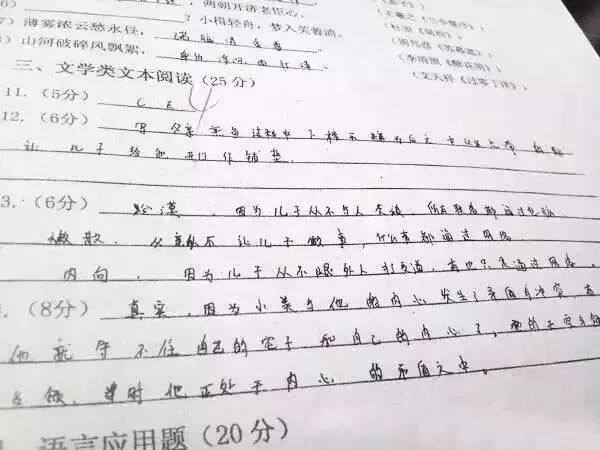
2、黑蚂蚁的飞行式:
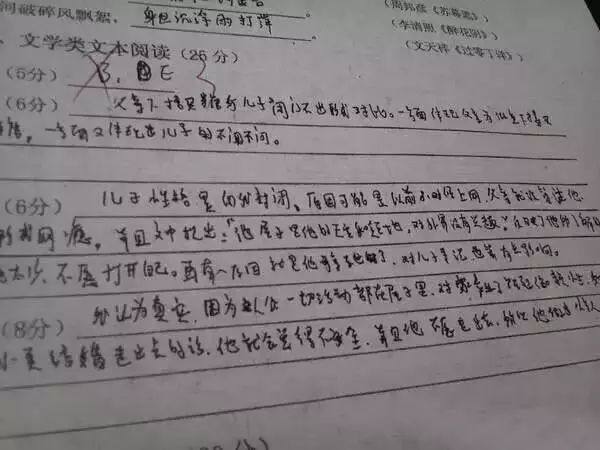
3、深坑寻幽式:
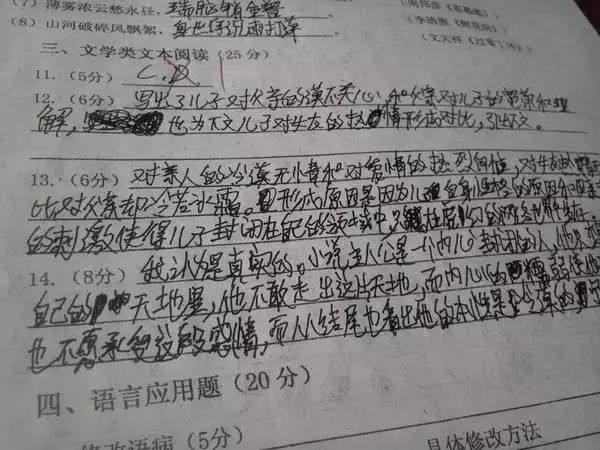
4、卑微的木柴式:
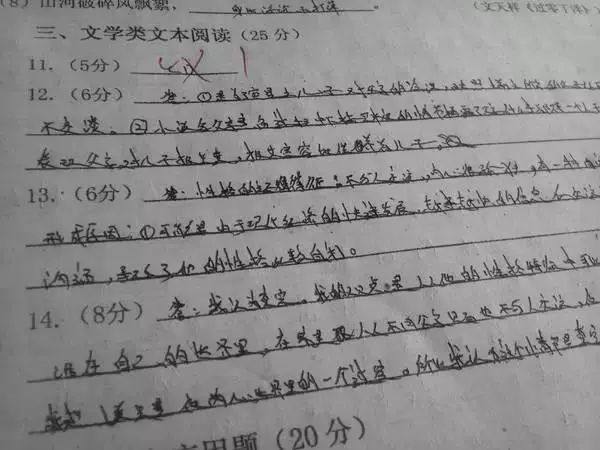
5、蓝色颤抖式:(中高考理论上只能用黑色水笔)
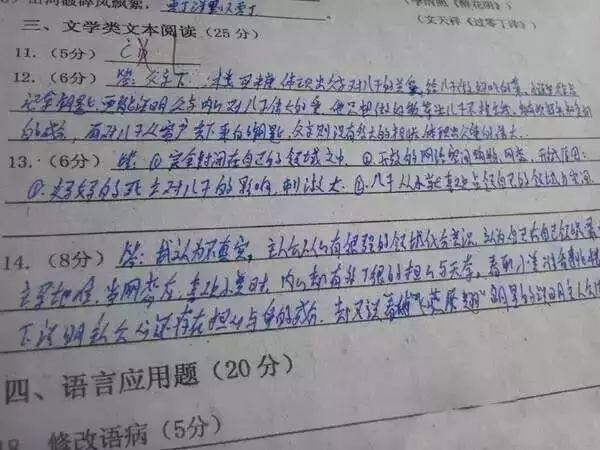
看了反面教材,中枪也不要怕,考试时最主要是把字写清楚。
小英老师建议我们的小学生:
1.可以写得不漂亮;
2.一定要能看清楚;
记住 ,你是参加考试,不是书法比赛!!!
阅卷者的建议,从阅卷的经验来看,主要有这么几点:
1.写楷书,也就是说尽量不要连笔;
2.字要写得稍大;
3.需要一大段文字时,写之前要排版。